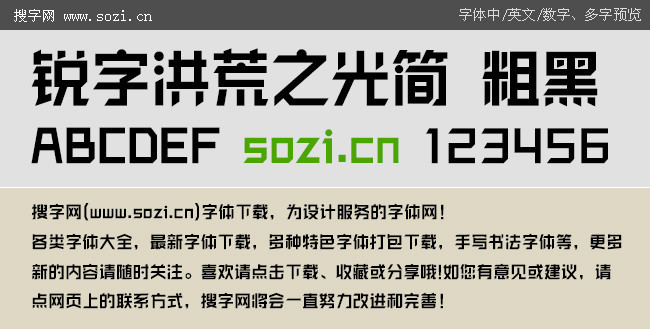
銳字洪荒之光簡 粗黑
搜字網(wǎng)提供一款銳字洪荒之光簡 粗黑中文字體下載,銳字洪荒之光簡 粗黑是銳字工房洪荒之光簡系列中字重第二粗黑一款藝術(shù)在體,字體穩(wěn)定,優(yōu)雅,堅固,看起來非常漂亮,整體效果非常均勻,可以應(yīng)用于廣告設(shè)計、名片設(shè)計、包裝印刷、產(chǎn)品設(shè)計等應(yīng)用。(本字體為個人非商用版,商用請聯(lián)系作者購買授權(quán))